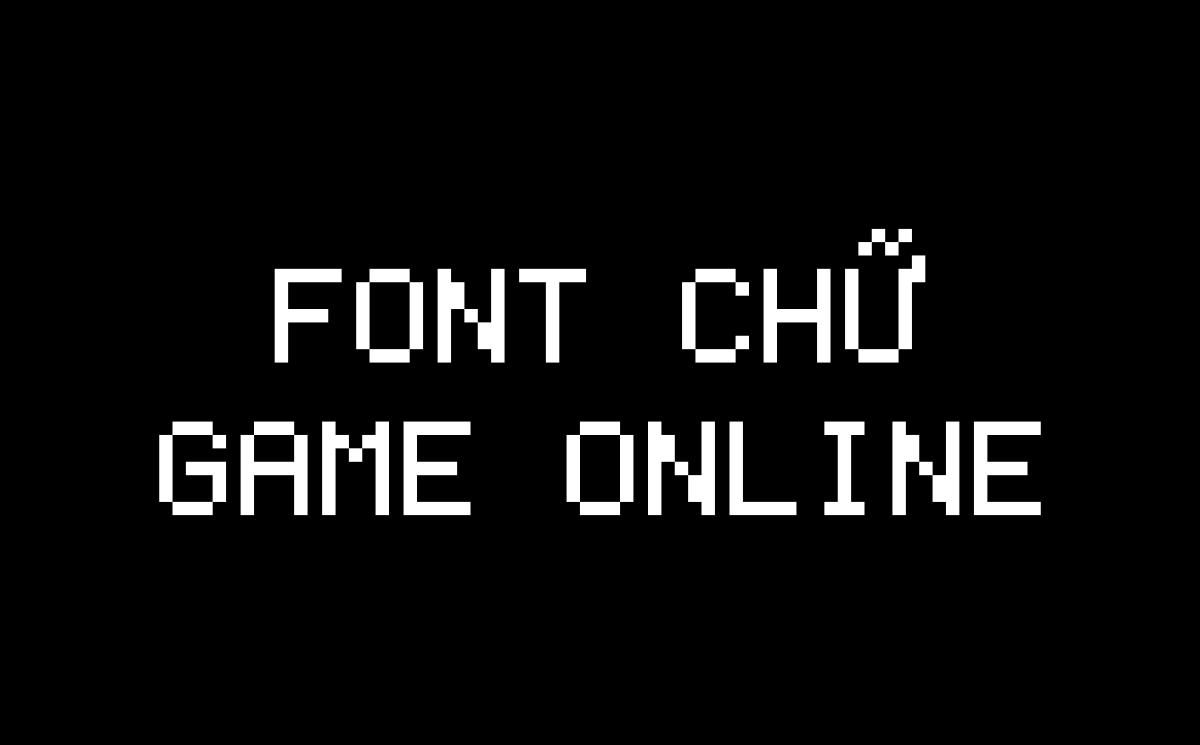
Trong thế giới thiết kế đồ họa hiện đại, việc lựa chọn một phông chữ thể hiện được bản sắc riêng, sự vững chắc và tính chuyên nghiệp là yếu tố then chốt tạo nên thành công cho mọi chiến dịch truyền thông. Font chữ SVN-Coder’s Crux ra đời như một giải pháp thiết kế hoàn hảo, mang phong cách hiện đại, góc cạnh và đậm chất kỹ thuật số. Với bản Việt hóa chuẩn xác từ SVN, bộ font này đáp ứng hoàn hảo mọi yêu cầu khắt khe trong các lĩnh vực tiên phong như thể thao điện tử (Esports), sản xuất game, ngành cơ khí chế tạo và công nghiệp xây dựng.</p>
Font Chữ Hiện Đại Cứng Cáp SVN-Coder’s Crux: Giải Pháp Thiết Kế Đỉnh Cao Cho Thể Thao Điện Tử, Game, Cơ Khí Và Xây Dựng
Ngành thiết kế sáng tạo đang ngày càng đòi hỏi những kiểu chữ không chỉ dừng lại ở mức độ dễ đọc mà còn phải truyền tải được năng lượng, tinh thần và đặc trưng của từng ngành nghề. SVN-Coder’s Crux là sự kết hợp tinh tế giữa tư duy thiết kế hình học (geometric) hiện đại và phong cách pixel/techno cổ điển nhưng đã được làm mới để phù hợp với xu hướng đồ họa đương đại. Khác với những phông chữ mềm mại hay thanh lịch truyền thống, SVN-Coder’s Crux sở hữu các đường nét dày dặn, mảng khối vuông vức và các góc bo/cắt dứt khoát, mang lại cảm giác kiên cố, đáng tin cậy và tràn đầy năng lượng.
Đối với các nhà thiết kế đang tìm kiếm một quân bài chủ lực cho dự án thương hiệu mang tính bứt phá, SVN-Coder’s Crux chính là sự lựa chọn không thể bỏ qua. Sự linh hoạt của bộ font này thể hiện ở khả năng thích ứng cao trên cả các sản phẩm số hóa lẫn ấn phẩm in ấn cỡ lớn, từ đó giúp thương hiệu thu hút sự chú ý của khách hàng ngay từ cái nhìn đầu tiên.
1. Phong Cách Thiết Kế Hình Học Cứng Cáp Và Đậm Chất Kỹ Thuật
Điểm đặc trưng nổi bật nhất của SVN-Coder’s Crux chính là cấu trúc chữ mang tính hình học vô cùng vững chắc. Mỗi ký tự được xây dựng dựa trên những tỷ lệ chuẩn xác, với các đường nét ngang dọc thẳng thắn và các góc nối được xử lý vô cùng công phu. Độ dày của nét chữ (stroke weight) đồng đều, tạo nên cảm giác đầm tay, kiên cố và đĩnh đạc. Thiết kế này đặc biệt phù hợp để thể hiện các chủ đề liên quan đến công nghệ cao, máy móc, cấu trúc hạ tầng hoặc những lĩnh vực đòi hỏi sự chính xác tuyệt đối trong từng chi tiết.
2. Tối Ưu Visual Ấn Tượng Cho Lĩnh Vực Thể Thao Điện Tử (Esports) Và Game Design
Trong không gian truyền thông của thể thao điện tử và công nghiệp game, hình ảnh luôn cần có sự bứt phá, tốc độ và cảm giác tương lai (futuristic). SVN-Coder’s Crux đáp ứng xuất sắc yêu cầu này nhờ vẻ ngoài đậm chất sci-fi và hành động. Font chữ rất phù hợp để làm tiêu đề giải đấu Esports, logo đội tuyển game, thiết kế giao diện người dùng (UI/UX) cho trò chơi, hay các banner quảng cáo sự kiện livestream. Nhờ tính nhận diện cao và vẻ ngoài gai góc, font chữ giúp truyền tải trọn vẹn tinh thần chiến đấu mạnh mẽ và sự cuồng nhiệt của cộng đồng game thủ.
3. Giải Pháp Định Vị Thương Hiệu Cho Ngành Cơ Khí Chế Tạo Và Xây Dựng
Ngành cơ khí và xây dựng đòi hỏi ngôn ngữ thị giác phải thể hiện được sự bền bỉ, an toàn, sức mạnh và tính bền vững theo thời gian. SVN-Coder’s Crux đáp ứng chính xác những tiêu chí này nhờ hình khối chữ vuông vức như những khối bê tông hay thanh thép định hình. Font chữ được ứng dụng rộng rãi trong thiết kế logo công ty xây dựng, bảng hiệu công trình, bao bì vật liệu kỹ thuật, tem nhãn máy móc cơ khí, cũng như các tài liệu hồ sơ năng lực doanh nghiệp. Sự xuất hiện của SVN-Coder’s Crux mang lại niềm tin mạnh mẽ cho đối tác và khách hàng về năng lực thi công và chất lượng sản phẩm.
4. Bộ Ký Tự Việt Hóa SVN Chuẩn Xác Và Đầy Đủ Dấu Tiếng Việt
Một trong những điểm cộng lớn nhất của phiên bản SVN-Coder’s Crux chính là việc được việt hóa chỉn chu, tỉ mỉ. Đội ngũ SVN đã nghiên cứu kỹ lưỡng để thiết kế hệ thống dấu tiếng Việt (dấu sắc, huyền, hỏi, ngã, nặng, dấu mũ, dấu móc) sao cho hòa hợp hoàn hảo với phong cách tổng thể của font chữ gốc. Dấu câu không bị thô, không phá vỡ khoảng cách dòng (leading) và duy trì sự cân bằng tuyệt vời giữa các ký tự. Điều này giúp các nhà thiết kế Việt Nam tự tin sáng tạo các tiêu đề tiếng Việt dài mà vẫn giữ được tính thẩm mỹ cao nhất.
5. Khả Năng Hiển Thị Sắc Nét Trên Mọi Nền Tảng Và Chất Liệu In Ấn
SVN-Coder’s Crux được tối ưu hóa vector kỹ lưỡng, đảm bảo khả năng hiển thị sắc nét trên mọi độ phân giải màn hình từ Full HD, 2K cho đến 4K. Bên cạnh đó, khi đưa vào sản xuất thực tế như cắt chữ nổi mica, khắc laser kim loại trong ngành cơ khí, in bạt hiflex khổ lớn cho công trình xây dựng hay in áo đấu Esports, bộ font này vẫn giữ nguyên độ chi tiết mà không bị lỗi nét hay mất dạng. Tính đa dụng này giúp quy trình sản xuất truyền thông của doanh nghiệp diễn ra mượt mà và tiết kiệm thời gian chỉnh sửa.
Gợi Ý Ứng Dụng Thực Tế Của Font SVN-Coder’s Crux Trong Sáng Tạo Đồ Họa
Để khai thác tối đa sức mạnh thị giác của SVN-Coder’s Crux, các nhà thiết kế có thể kết hợp bộ font này vào nhiều dạng ấn phẩm khác nhau:
- Poster và Banner Giải Đấu Esports: Sử dụng SVN-Coder’s Crux cho các từ khóa chính, tên giải đấu hoặc số tiền thưởng để tạo sự chú ý tức thì.
- Thiết Kế Identity Ngành Cơ Khí: Đưa font chữ vào hệ thống nhận diện thương hiệu như card visit, catalogue thiết bị, catalogue linh kiện phụ tùng.
- Bảng Hiệu Công Trình Xây Dựng: Tạo các bảng cảnh báo an toàn, bảng thông tin dự án bất động sản và hạ tầng với độ đọc hiểu từ xa cực tốt.